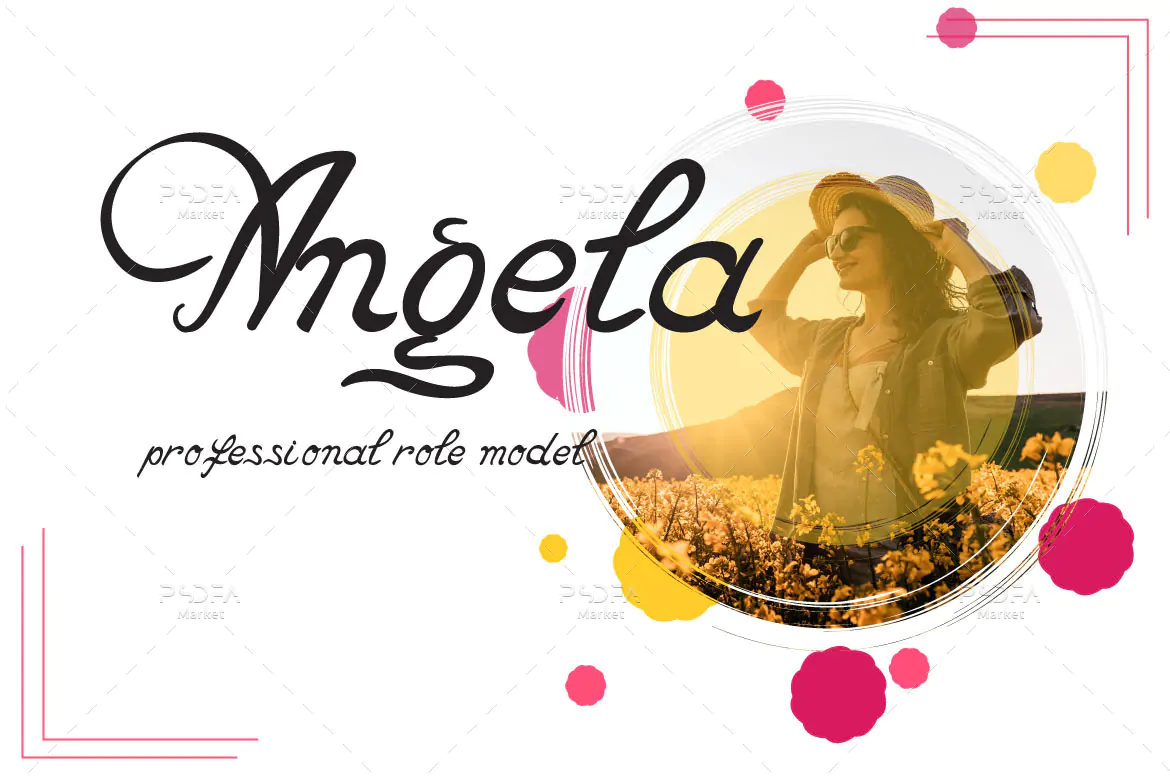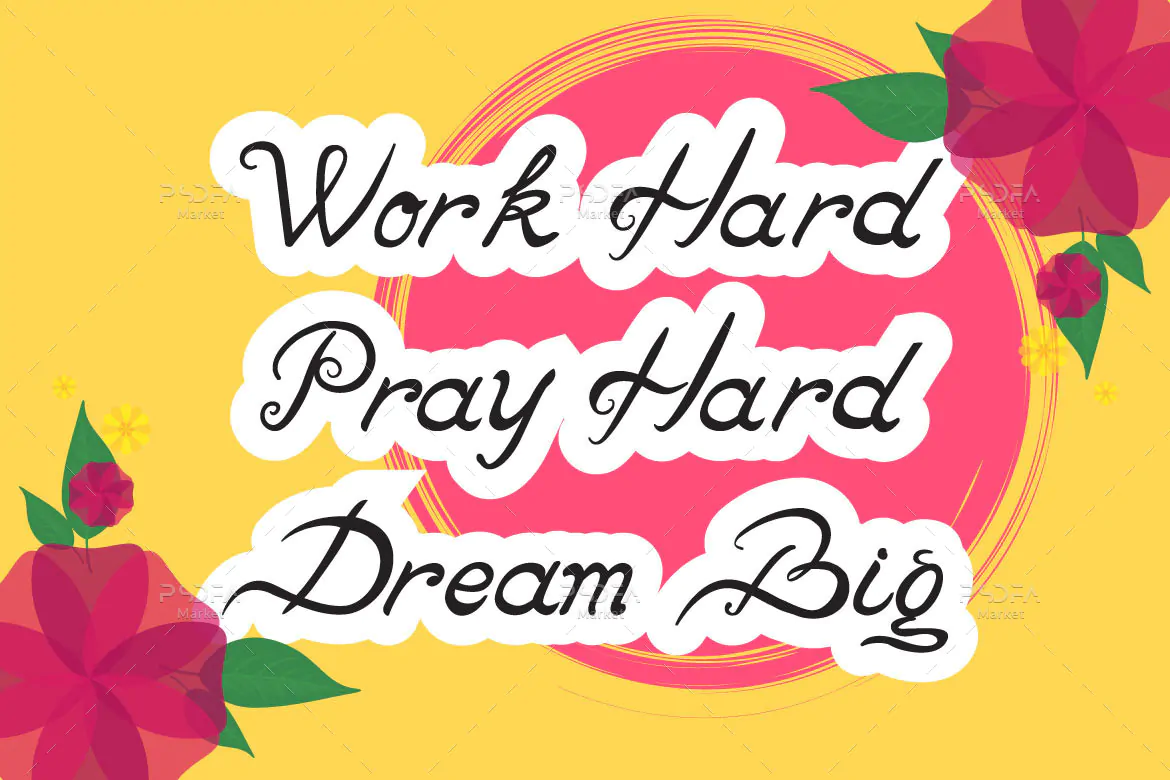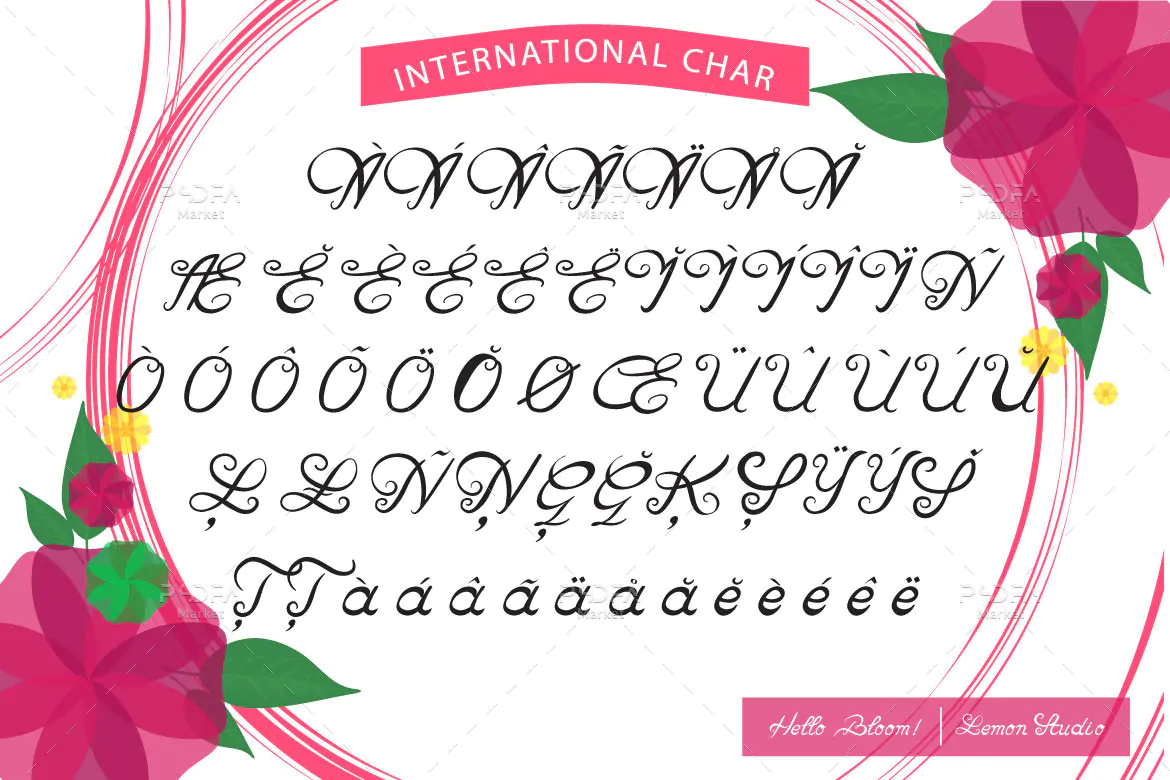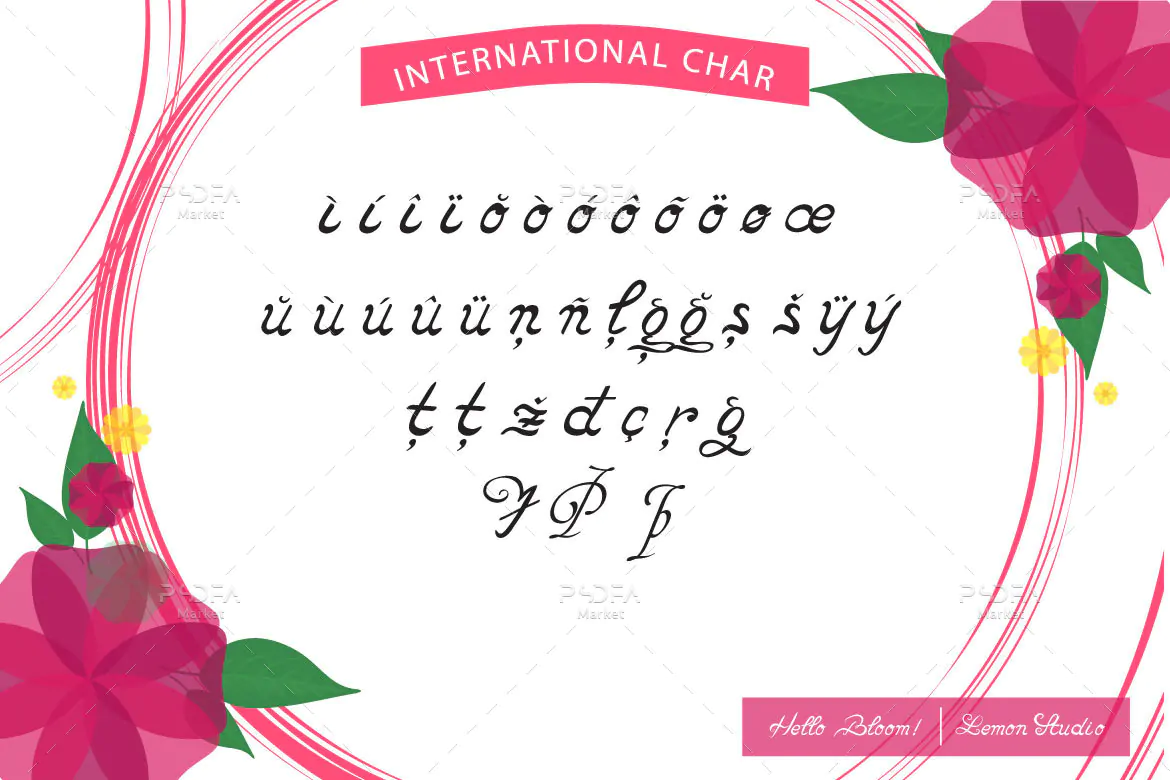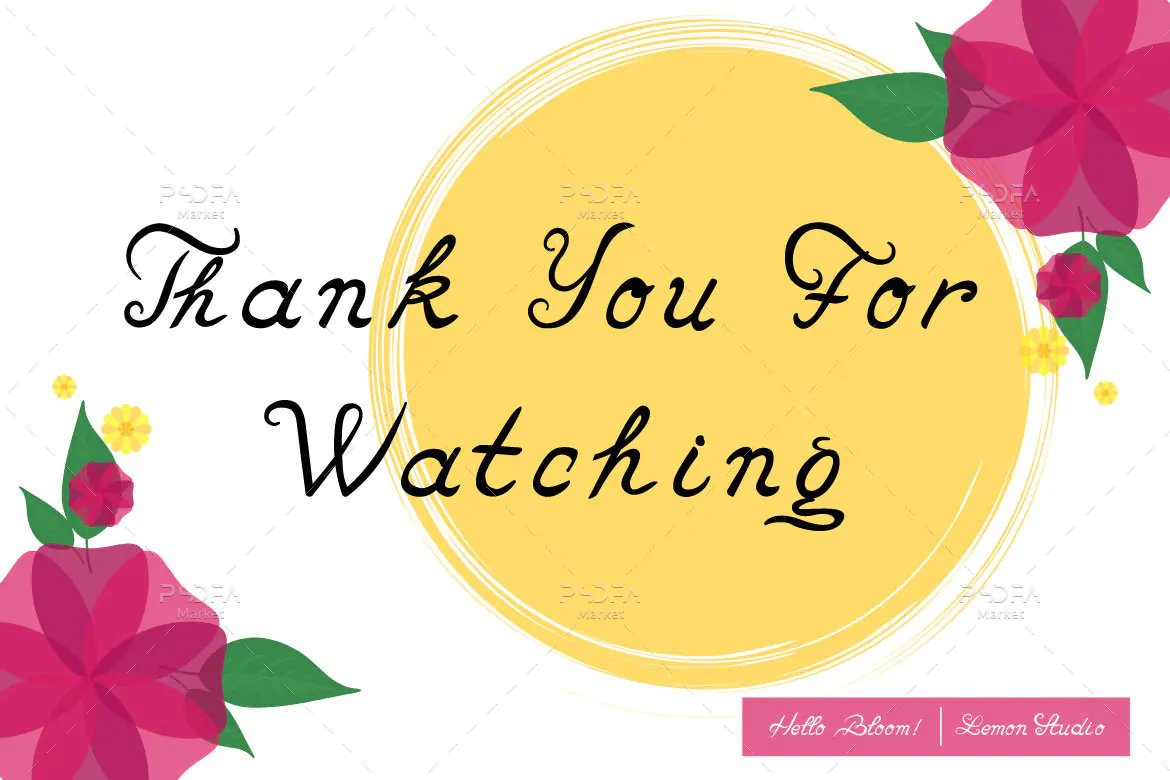
فونت دستنویس مدرن و زیبای Hello Bloom
فونت دستنویس مدرن انگلیسی
فونت دستنویس مدرن و زیبای Hello Bloom یک اسکریپت فونت فوق العاده زیبای انگلیسی است که میتوانید از آن در طرحهای گرافیکی مختلف به خصوص طراحی انواع کارت استفاده کنید. این فونت زیبا با وزن معمولی طراحی شده است و مناسب جهت استفاده در طراحی انواع پوستر، کارت تبریک، کارت عروسی، بسته بندی محصولات، آرایشی و بهداشتی و … میباشد.